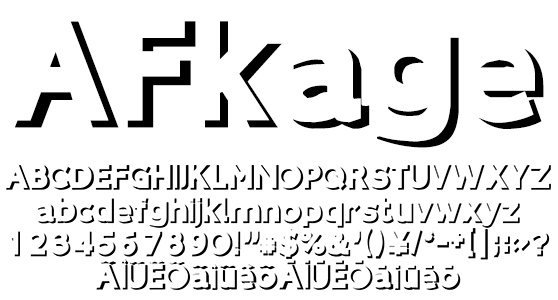
影文字欧文 AFkage
AFkage
バックカラーを活かす影文字は、イメージを与えるためにご用意いたしました。視認性を抑える事で注目を集める逆効果に期待できます。動画テロップ後の配信、字形装飾が困難な Web Serverへのアップロード、フォント共有サーバー利用、PDFエンベッド、印刷やロゴなど作成と登録、印影や彫刻、画像化後ソフトへのバンドルなど商用利用できます。